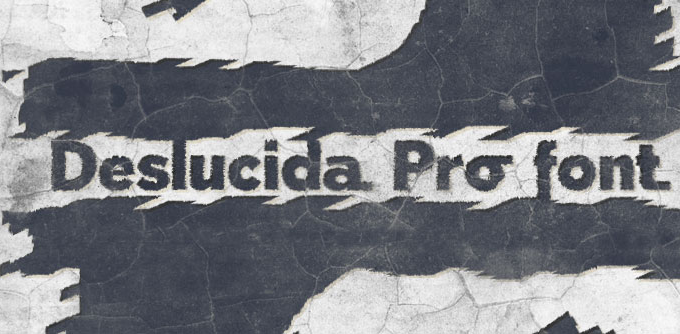
A Deslucida é uma nova opção de tipo sem serif que traz a agilidade e versatilidade para qualquer projeto visual. Com sua categoria de sans-serif, esta fonte foi projetada pelo designer Hamilton, oferecendo um estilo moderno e clean que se adequa perfeitamente à necessidades dos designers digitais atuais. Uma das características mais interessantes da Deslucida é a disponibilidade do versão comercial com Itálico Verdadeiro e recursos Open Type. Isso permite uma maior personalização e flexibilidade, permitindo aos designers criarem textos ainda mais complexos e elaborados sem precisar recorrer a fontes adicionais. Com uma variedade de aplicações e um design limpo, a Deslucida é ideal para qualquer projeto que exija modernidade e simplicidade. Além disso, sua versão comercial traz benefícios únicos como itálico verdadeiro e recursos Open Type, oferecendo aos designers a flexibilidade necessária em seus projetos, seja para criações de textos mais elaboradas ou para uma maior customização das fontes. Seja você um designer gráfico atento às tendências da indústria digital ou um profissional que valoriza versatilidade e eficiência, a Deslucida é uma escolha ótima para seus projetos.